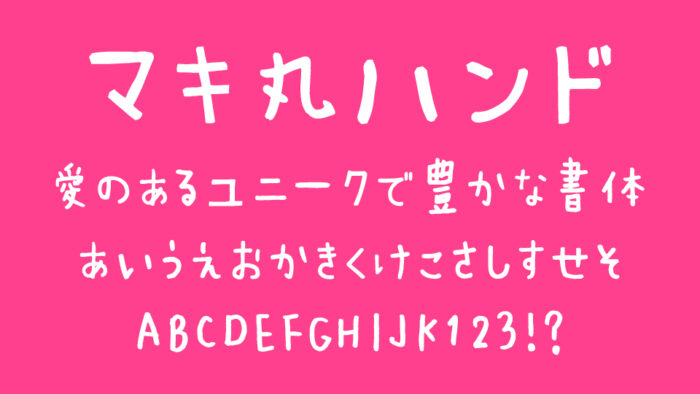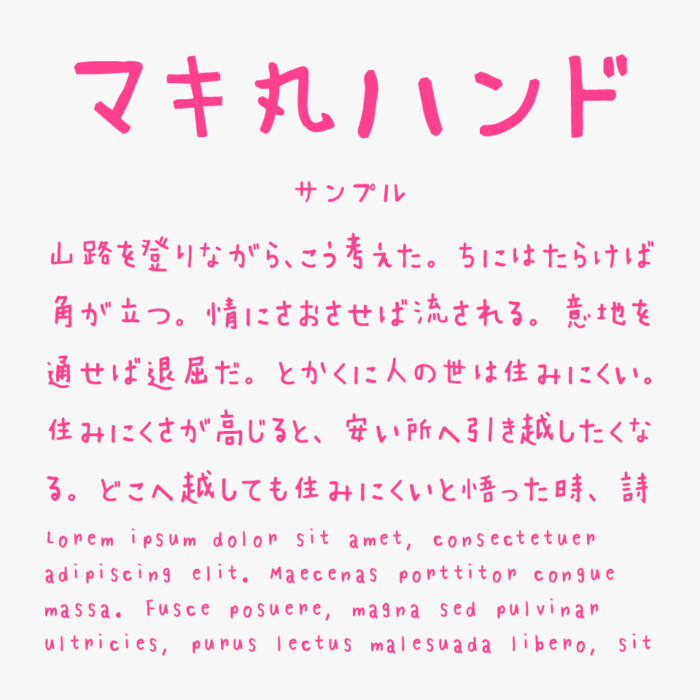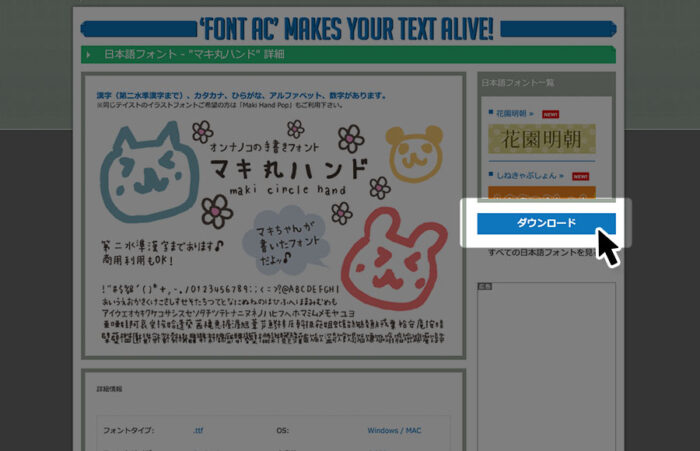
マキ丸ハンド
マキ丸ハンドフォントは、やわらかく丸みを帯びた文字がラフに書いたような親しみを感じさせてくれる手書きフォントです。
文字の太さが均一ではなく、ランダムな揺らぎががリアルな手書きぽさを表現されていて、特にかな文字が少しこぶりになっているので可愛らしく、女性の手書き文字らしさのあるフォントです。